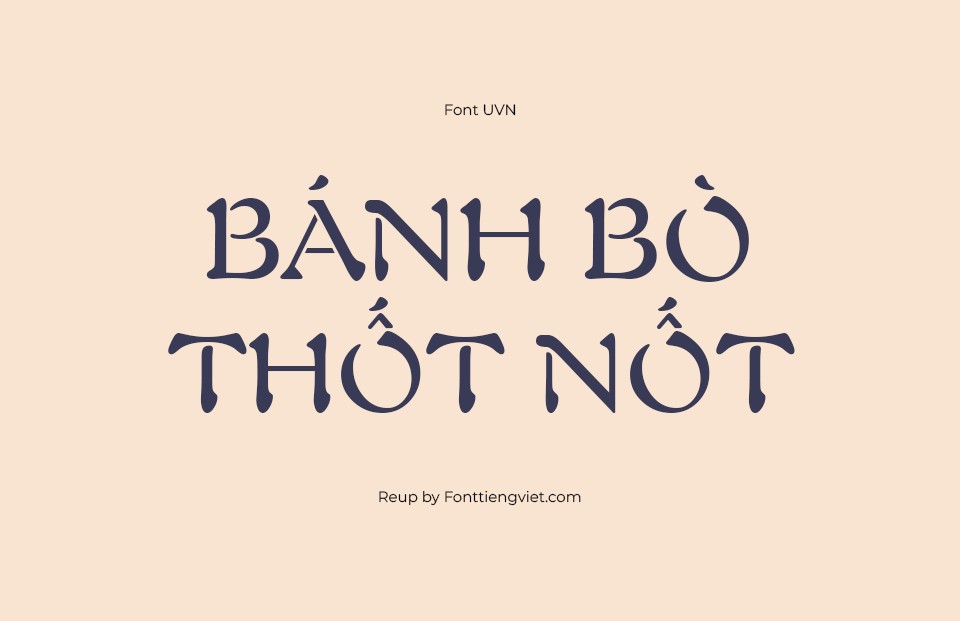
Tải Ngay Font việt hóa UVN Mang Cau Miễn Phí Cho Thiết Kế Giáo Dục
Trong cộng đồng thiết kế đồ họa tại Việt Nam, việc tìm kiếm một bộ Font Chữ vừa mang nét truyền thống vừa đảm bảo tính thẩm mỹ là điều rất quan trọng. Font việt hóa UVN Mang Cau chính là giải pháp hoàn hảo, được tinh chỉnh kỹ lưỡng để phù hợp với bảng mã Unicode, giúp người dùng dễ dàng soạn thảo các nội dung tiếng Việt mà không lo lỗi font. Với phong cách thanh mảnh và nét chữ mềm mại, bộ font này đang trở thành lựa chọn ưu tiên cho các dự án sáng tạo trong môi trường học đường.
Đặc điểm nổi bật của Font việt hóa UVN Mang Cau
Thiết kế tinh tế và gần gũi
Font việt hóa UVN Mang Cau sở hữu những đường nét thanh thoát, gợi nhớ đến phong cách trình bày văn bản trang trọng nhưng vẫn giữ được sự gần gũi. Điểm mạnh của bộ font này là khả năng hiển thị rõ ràng trên cả bản in và màn hình kỹ thuật số. Nhờ vào sự tỉ mỉ trong quá trình việt hóa, các dấu câu tiếng Việt được đặt ở vị trí chuẩn xác, giúp tổng thể văn bản trông hài hòa và chuyên nghiệp hơn rất nhiều so với các font mặc định.
Ứng dụng đa dạng trong học tập
Các thầy cô giáo và học sinh có thể sử dụng Font việt hóa UVN Mang Cau để thiết kế bài giảng điện tử, làm báo tường hoặc trình bày các tiểu luận. Sự nhẹ nhàng của font chữ giúp người đọc không bị mỏi mắt, đồng thời tạo nên một không gian học tập đầy cảm hứng. Ngoài ra, font cũng rất phù hợp để làm thiệp chúc mừng hoặc các biểu mẫu khen thưởng trong nhà trường.
Cách sử dụng và cài đặt hiệu quả